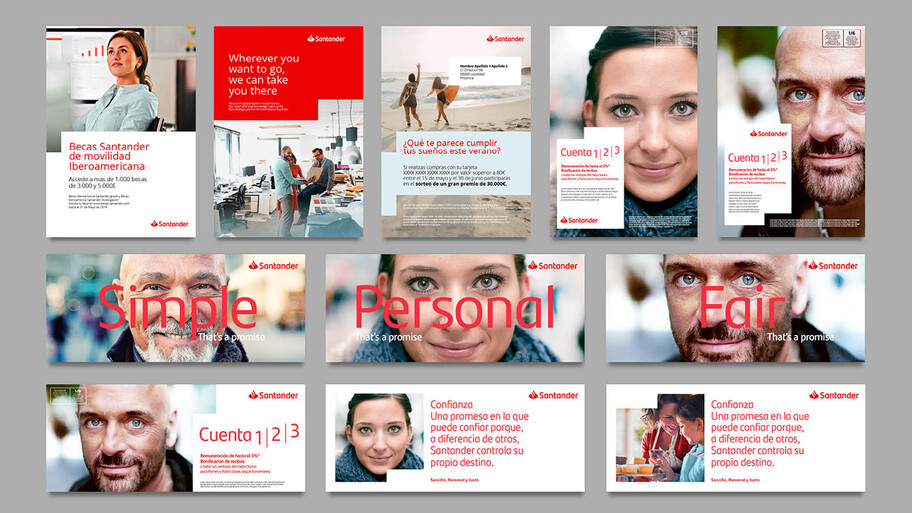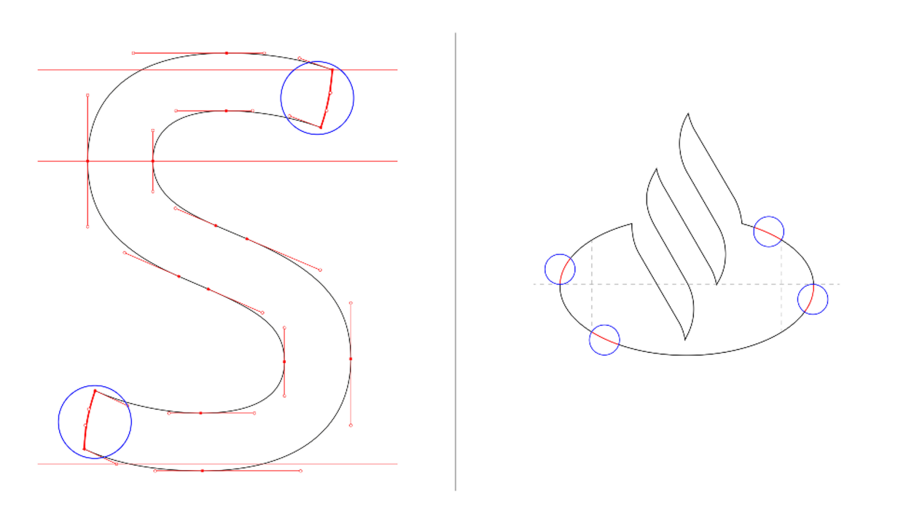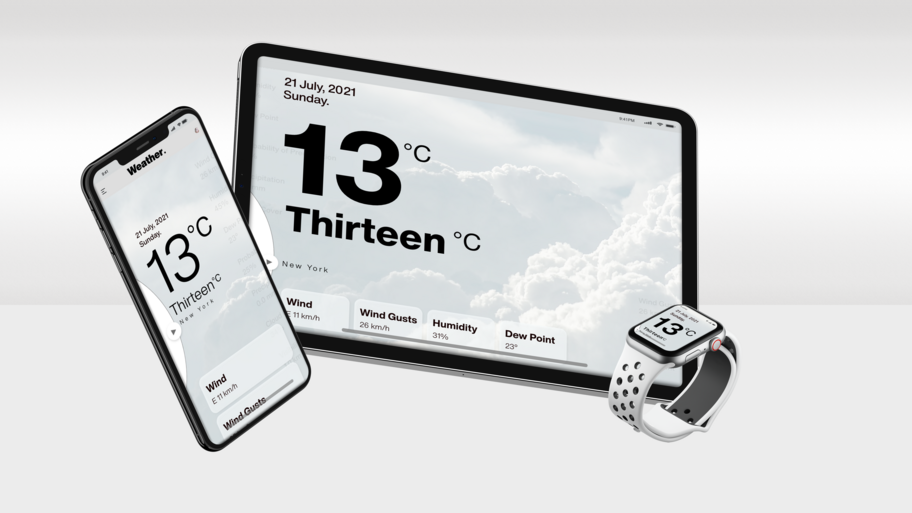
Vertrauen. Sicherheit. Flexibilität.
Da sich der Markt für Finanzdienstleistungen mehr und mehr zum digitalen Business entwickelt, mit einer enormen Bandbreite innovativer Produkte, ist die visuelle Identität Ihre Marke und damit deren Wiedererkennbarkeit entscheidend für den Aufbau einer starken, dauerhaften Kundenbeziehungen.
Berührungslos, aber greifbar.
Die Tage der Vis-à-vis-Bankgeschäfte sind gezählt. Auch wenn bestimmte Dienstleistungen weiterhin in Filialen abgewickelt werden, finden die alltäglichen Bankgeschäfte überwiegend digital und in den meisten Fällen auf einem Mobilgerät statt. Dies bedeutet, dass Ihre Marke die Kundenerlebnisse nicht mehr nur begleitet: Das Kundenerlebnis ist Ihre Marke.
Damit Marke und Erlebnis im Einklang stehen und positiv wahrgenommen werden, spielen Benutzerführung, visuelle Identität und Typografie eine tragende Rolle. Eine unverkennbare, gut lesbare und technisch ausgereifte Schrift überbrückt die Diskrepanz zwischen einer Marke, die Kunden lieben, und Erlebnissen, bei denen die Kunden „kein gutes Gefühl“ haben. Und weil sich Branche und Technik ständig weiterentwickeln, brauchen Finanzmarken ein intelligentes Konzept für ihre Hausschrift, sodass diese den Entwicklungen nahtlos folgen kann.
Santander Next - a custom font by Monotype Studio.
Vertrauen ist alles.
In dem Maße, wie sich unsere finanziellen Aktivitäten ins Digitale verschieben, verlagert sich auch der Kampfplatz der Betrüger. Unser Online-Leben birgt potenzielle Fallstricke, die unserer Daten, die Sicherheit unserer Privatsphäre und unserer finanziellen Transaktionen gefährden, zum Beispiel durch Phishing, Identitätsdiebstahl oder Fake-Marken, die versuchen, Kunden in eine Falle zu locken.
Auch wenn Behörden, Netzbetreiber und schützende Software massiv gegen Onlinebetrug vorgehen: Die etablierte Identität einer Marke kann eine starke erste Verteidigungslinie aufbauen. Weniger empfehlenswert: Eine visuelle Identität, die auf leicht zugängliche Systemschriften oder Open-Source-Fonts basiert, und von Betrügern sehr einfach nachgebaut werden kann.
Eine Marke, die auf eine ausgefallene Lizenzschrift setzt oder sich eine eigene Exklusivschrift entwickeln lässt, ist nicht nur für Verbraucher leichter als Original zu erkennen: Sie bietet auch weniger Angriffsfläche für Betrügereien.
Schriften. Offen für alle.
So wie Gebäude für jeden Menschen zugänglich sein sollten, erwarten die Verbraucher auch im Netz einen barrierefreien Zugang. Die EU-Richtlinie WCAG 2.1 für barrierefreie Websites von öffentlichen Einrichtungen trat im Dezember 2016 in Kraft und ist seit September 2020 geltendes Recht in den Mitgliedsstaaten; seit September 2021 gilt sie auch für mobile Anwendungen. Neben den Behörden betrachten auch viele Unternehmen das Recht der uneingeschränkten Teilhabe an digitalen Dienstleistungen als eine Grundvoraussetzung für Inklusion, und deshalb folgen sie den EU-Empfehlungen.
Schriften spielen eine große Rolle, wenn es um Barrierefreiheit in der visuellen Kommunikation geht … angefangen von der Gestaltung der Buchstaben und Ziffern, über deren Kontrast und Laufweite, bis hin zur typografischen Gestaltung von Websites oder App-Interfaces. In Deutschland definiert die DIN 1450 die leserliche Darstellung von Texten im öffentlichen Raum, in Büchern, Magazinen und Zeitungen. Bei der Kommunikation im Netz hat sich die Benutzung von Webfonts durchgesetzt. Die Verwendung statischer Texte – eingefroren in .gif-, .png- oder .jpg-Abbildungen – ist aus Sicht der Barrierefreiheit ein No-Go, weil sie sehbehinderte Menschen ausschließt, die auf maschinelle Texterkennung, gesprochene Inhalte und Sprachsteuerung angewiesen sind.
Helvetica Now Variable
Lösungen für eine Welt im Wandel.
Unsere Lösungen verbinden unser Fachwissen mit unserer Erfahrung, um Marken Werkzeuge an die Hand zu geben, mit denen sie agil wirtschaften und dauerhafte Kundenbeziehungen aufbauen können.
Monotype Fonts.
Mit dem größten Angebot an Schriften, darunter viele preisgekrönt, und dem Zugang zu den angesagtesten Foundries und Schriftentwerfern der Welt, versetzt Monotype Fonts professionelle Designer in die Lage, weniger Zeit mit administrativen Aufgaben zu verbringen und stattdessen alle Energie in die Gestaltung aussagekräftiger Markenerlebnisse zu stecken.
Wesentliche Merkmale
• Die besten Schriften, Typedesigner und Foundries der Welt.
• Zuverlässige und sichere Schriftverwaltung.
• Integration in die Tools, die Sie täglich nutzen.
• Kontrollierte jährliche Kosten.
Unser Studio ist das Herzstück der größten Schriftbibliothek der Welt, angetrieben von der Leidenschaft für Fonts. Wir bieten eine Reihe von Dienstleistungen an, die es Marken jeder Größe ermöglichen, ihre Stimme durch Schrift zum Ausdruck zu bringen, damit Menschen sie sofort erkennen und sich mit ihnen identifizieren.